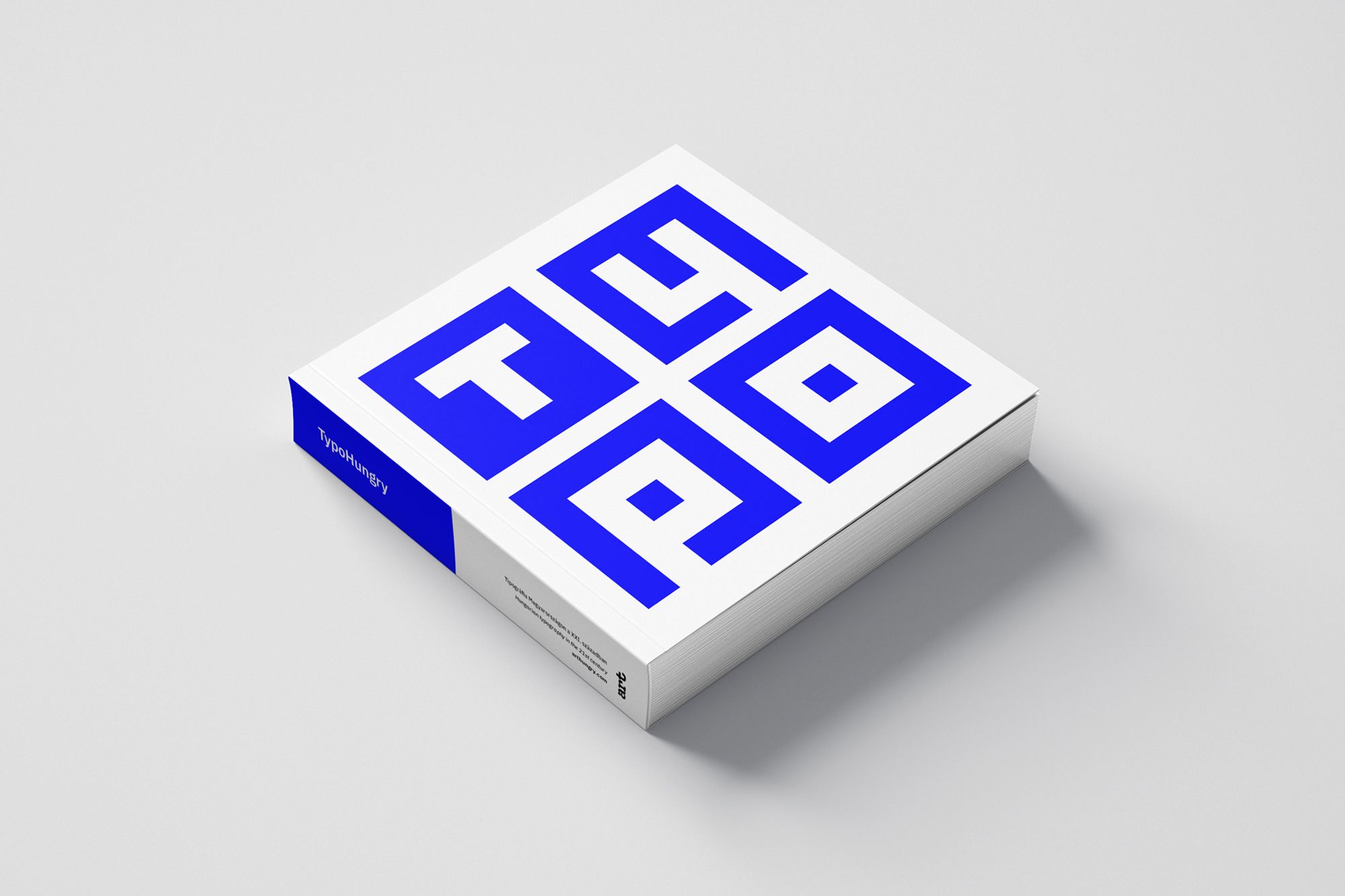
Ma nyílt meg a nevezés az ArtHungry idei első, TypoHungry – Tipográfia Magyarországon a XXI. században nevet viselő pályázatára, amelyben az elmúlt húsz év legjobb hazai tipográfiai munkáit keresik. A szakmai zsűri által kiválasztott projektekből később egy kötet is készül, amely egy több részes, művészeti kiadványokból álló sorozat első darabja. Tábori-Simon Joséval, az ArtHungry alapítójával beszélgettünk.
Mi adta az ötletet az exkluzív könyvsorozathoz?
Mindig is fontosnak tartottam, hogy a megrendelésekre készült tervezőgrafikai munkáim mellett saját kiadványokon is dolgozzak, így az elmúlt húsz évben több kiadó társalapítója voltam, amelyekkel főleg divat- és popkulturális magazinokat terveztünk és jelentettünk meg. Régi vágyam volt, hogy az ArtHungry portfóliós gyűjtőoldalra feltöltött nívós projekteknek nyomtatott megjelenést is biztosítsunk, mert meggyőződésem, hogy a mai túlpörgetett digitális világban van még létjogosultsága a szépen kivitelezett, könyvespolcra tehető és kézbe vehető kreatív albumoknak.
A kiadónk már adott volt, ráadásul az ArtHungry felületén az elmúlt évek során rengeteg szuper munka gyűlt össze. A tervezőművészet – érthetetlen módon – eléggé alulreprezentált a hazai könyvpiacon, így jött az ötlet 2020 elején, hogy elindítsunk egy pályázat- és kiadványsorozatot, amelyben a kétezres évek legnívósabb, nemzetközi léptékkel is kiugróan magas szakmai színvonalú, hazai tervezőgrafikai projektjeit gyűjtjük össze.
A művészeti kiadványsorozat első három része a tipográfiát, a logótervezést és az ikontervezést fogja a fókuszba állítani. Miért pont a tipográfiával indítjátok a sort?
Úgy gondolom, hogy az elmúlt két évtized tervezőművészetében a robbanásszerű digitális átállás és a szuperszonikus fejlődés főleg a tipográfia területén érhető tetten. A számítógépek egyre felhasználóbarátabb működése és a különböző grafikai szoftverek megjelenése a kilencvenes években új dimenziókat nyitott meg a betűtervezők előtt is. Az újra reneszánszát élő experimentális tipográfia épp a kilencvenes évek végén és a kétezres évek elején élte fénykorát. A mobil eszközök és platformok megjelenése ismét újabb trendeket hozott magával – az újklasszikus betűcsaládok megjelenését követően a fiatal tervezők manapság újra felfedezik a hetvenes évek pszichedelikus betűit. Mindez nem csak nemzetközi színtéren zajlik: az internetnek és a gyors információcserének köszönhetően ez a folyamat itthon is ugyanúgy megfigyelhető. Elég izgalmas válogatás várható a betűtípusok terén, de egyébként bármilyen betű alapú projektet szívesen várunk: jöhetnek a legkülönbözőbb tipográfiai jelek, ligatúrák, monogramok, kalligráfiák vagy akár experimentális tipográfiai munkák, sőt, graffitik is.
A későbbiekben külön pályázatot szeretnénk szentelni majd a kétezres években készült hazai kiadványoknak, magazinoknak is, de tervbe van véve például a UI/UX- és játéktervezési projekteket összegyűjtő albumok megjelentetése is.
Ahogyan az összes tervezett kötet esetében, úgy az elsőben megjelenő munkákat is egy kilenctagú szakmai zsűri választja ki. Kiket sikerült megnyerni a tipográfiai pályázathoz?
Nagyon fontos volt, hogy olyan szakembereket kérjünk fel a kurátori feladatokra, akik az adott kategóriában otthonosan mozognak, itthon és nemzetközi szinten is elismertek szakmailag. A kiadványokban a zsűritagok munkái is helyt kapnak, ezért kiválasztásuknál az is szempont volt, hogy kik azok a hazai tervezőgrafikusok és betűtervezők, akik semmiképpen nem maradhatnak ki egy ilyen jellegű kötetből. A TypoHungry kiadvány esetében Balla Dóra, a MOME grafikai tanszékének docense az experimentális vonalat képviseli a zsűriben. Boskovitz Oszkár és Szegi Amondó, a Magyar Betűtársaság alapítói több intézményben is oktatják a betűtervezést, betűtípusaikat nemzetközi szinten is használják. Halasi Zoltán munkáit már számos szakmai díjjal elismerték, tipográfiát tanít több hazai egyetemen is. Kőrös János a Halisten Stúdió tagjaként főleg kézzel rajzolt betűiről és kalligráfiáiról ismert. Kiss Miklóst sem kell bemutatni; nemzetközi szinten elismert vizuális művész, jellegzetes ligatúráival biztos, hogy mindenki találkozott már. Frank Béla és Katyi Ádám pedig a legismertebb hazai új generációs betűtervezők közé tartoznak, mindkettőjüknek saját digitális „betűöntödéje” van.
Bő húsz éve vagy már a szakmában. Számos magazinos, lemez- és albumborítós munkád, illetve klassz, informatív ikonjaid mellett többek között a Design Hét Budapest rendezvénysorozat számára is terveztél már betűt. Te hogyan látod az elmúlt évek tipográfiai fejlődését itthon?
Alkotóként a saját bőrömön tapasztaltam az ezredfordulós technikai, digitális forradalmat. Az enyém az a generáció, amelynek tagjai a főiskolán még kézzel festettek betűt, a tus- és csőtoll mellett Letraset sablonokat használtunk. A számítógépek megjelenésekor QuarkExpress-ben tördeltünk, Freehandben terveztünk betűtípusokat, majd Fontographerben magyarítottunk és generáltunk fontkészleteket. Az online kommunikációt betárcsázós modemekkel kezdtük és órákat töltöttünk el levilágító stúdiókban azzal, hogy nagyítóval vizsgáljuk a filmeket és a kromalinokat a nyomdai gyártás előtt.
Mindezekkel a hátam mögött úgy látom, a hazai tipográfia fejlődése talán a kétezertízes évekre vette fel a ritmust a nemzetközi vérkeringéssel. A gazdasági válságok ellenére – még a jelenleg tomboló pandémia kellős közepén is – folyamatosan frissülnek az eszközeink, egyre egyszerűbben kezelhető szoftvereket használunk betűtervezésre is, egyre jobb az oktatás és ennek eredményeként virágkorát éli a tipográfia nemcsak külföldön, de itthon is.
Látsz-e különbséget a ma és a tíz-húsz évvel ezelőtt alkotó betűtervezők stílusa között itthon és külföldön?
Nem választanám külön a hazai és külföldi tipográfusokat, mert ahogy az imént említettem, a kétezres években már sokkal könnyebb volt naprakésznek lenni itthon is, főleg az internet miatt. Ha a tipográfiai és egyben a tervezőgrafikai trendeket nézzük, az ezredfordulós kísérleti trashtipográfia-dömping után egy hosszan tartó, pontosan szerkesztett, klasszikus fontokat újraszerkesztő időszakra emlékszem. Az elmúlt években pedig azt látom a különböző szakmai közösségi platformokon, hogy az általános popkulturális retróhullám, vagyis a hetvenes- és a nyolcvanas évek újrafelfedezése megy nagyon még mindig a fiatal betűtervezők körében.